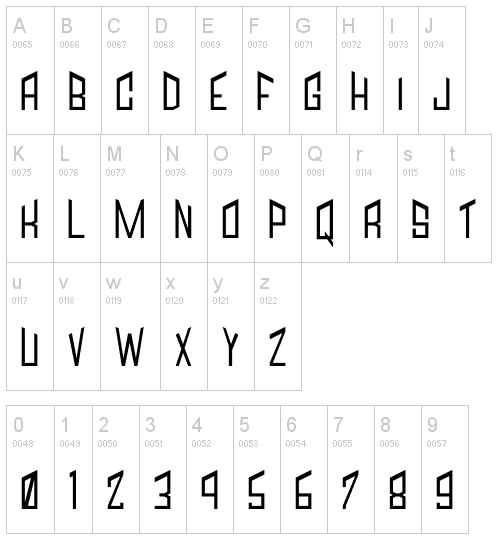
Font Design: Jagged
Ecco di nuovo l’appuntamento mensile con Font Design, nel quale presentiamo un nuovo font da scaricare gratuitamente.
Il font Jagged realizzato da Hanifa Rinaldi è squadrato e ha la particolarità di avere degli angoli alle estremità destra e sinistra nel lato superiore della singola lettera.
Ecco tutti i caratteri di questo font: